TikTok Sans. Бесплатный фирменный шрифт известной соцсети имеет 14 стилей. Это вариативный гротеск с небольшой геометричностью и позитивным характером.
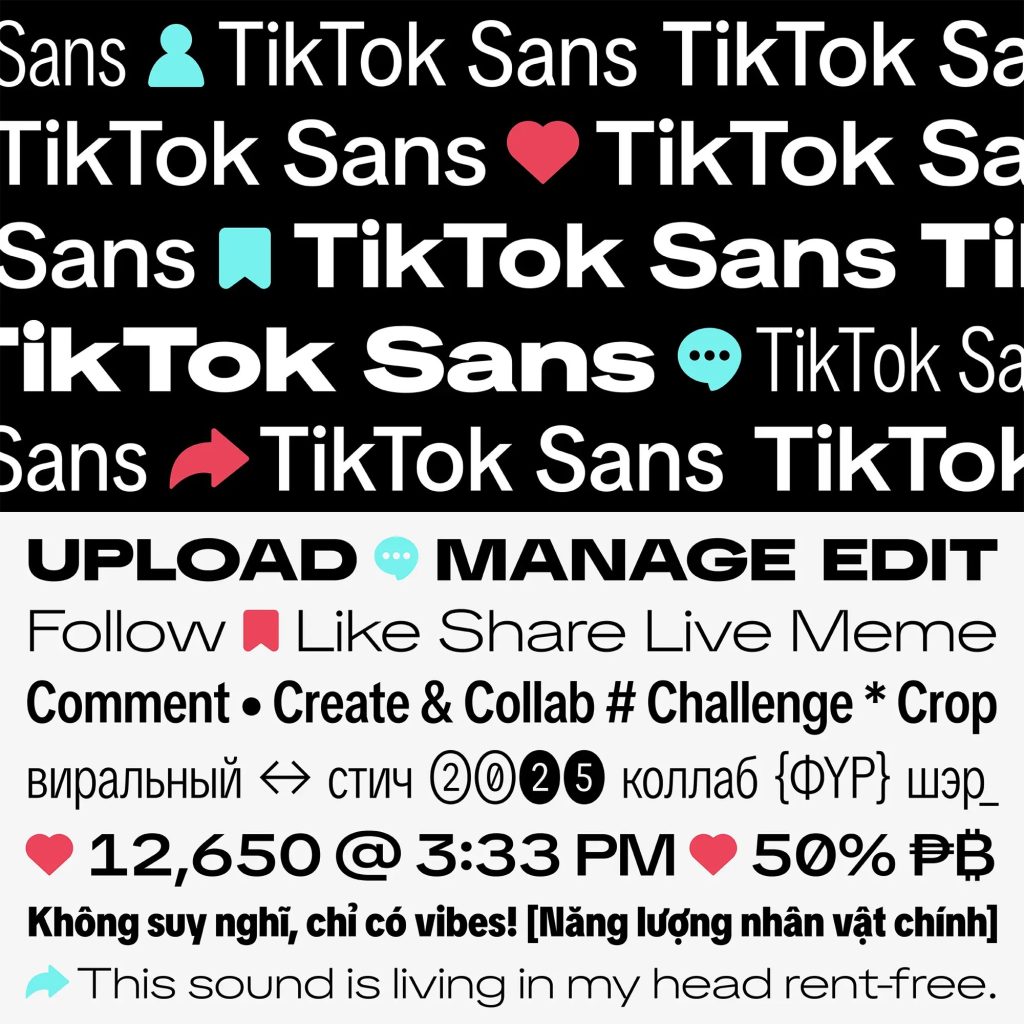
Martian Grotesk. Современный вариативный гротеск «Злых Марсиан» содержит 63 статичных начертания и изменяется по толщине и ширине. Оптимизирован для веба.
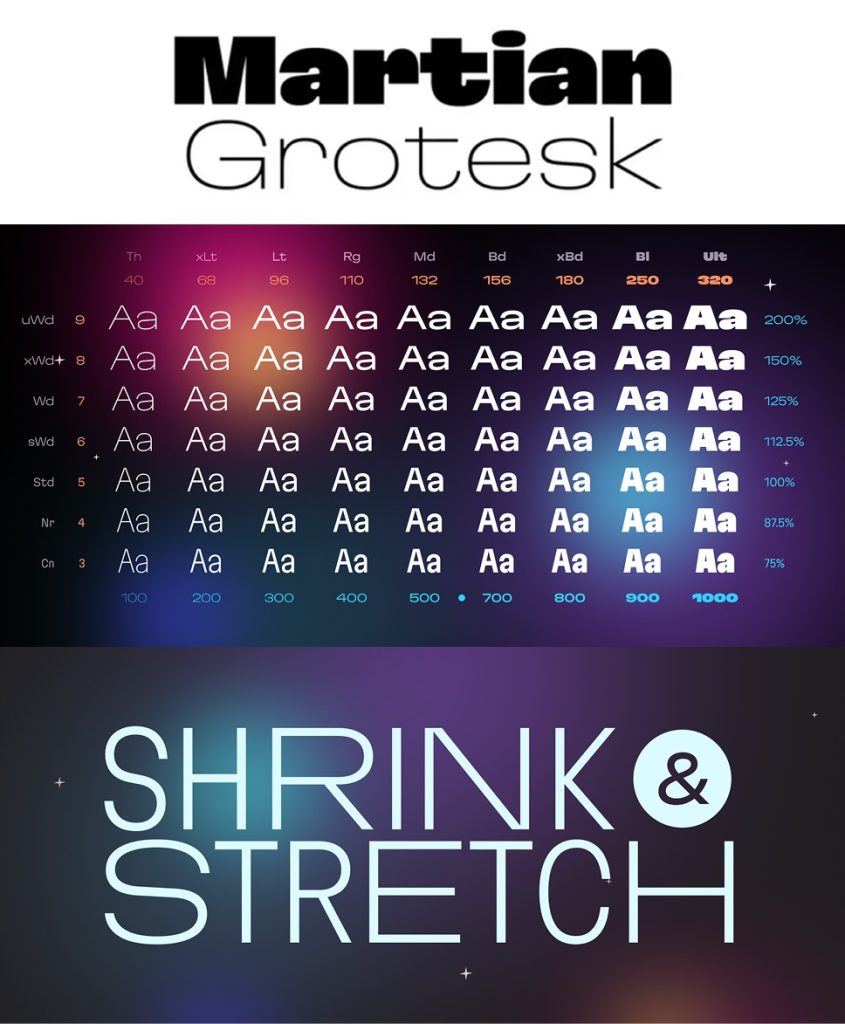
Лето. Вариативный декоративный гротеск с семью начертаниями и жизнерадостным характером.
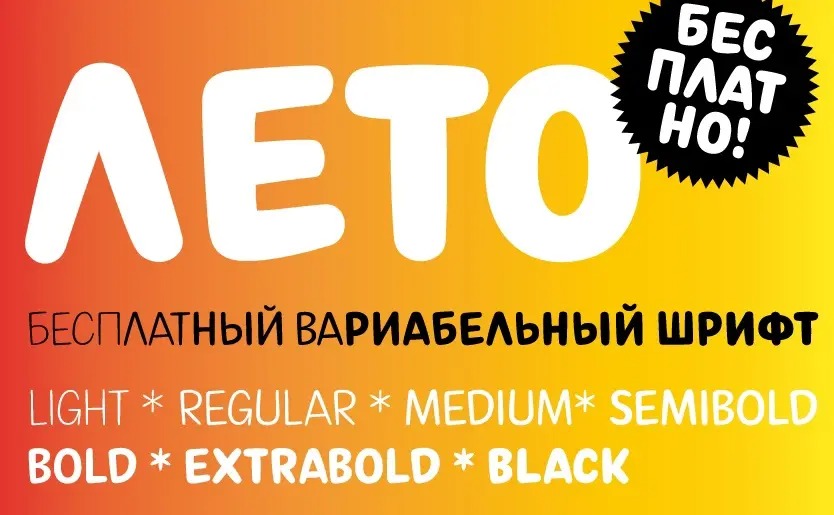
Noise. Лёгкий жизнерадостный гротеск в двух вариантах: базовом и со сплошными декоративными заливками. Подойдёт для упаковок, плакатов, брендинга и детских проектов.
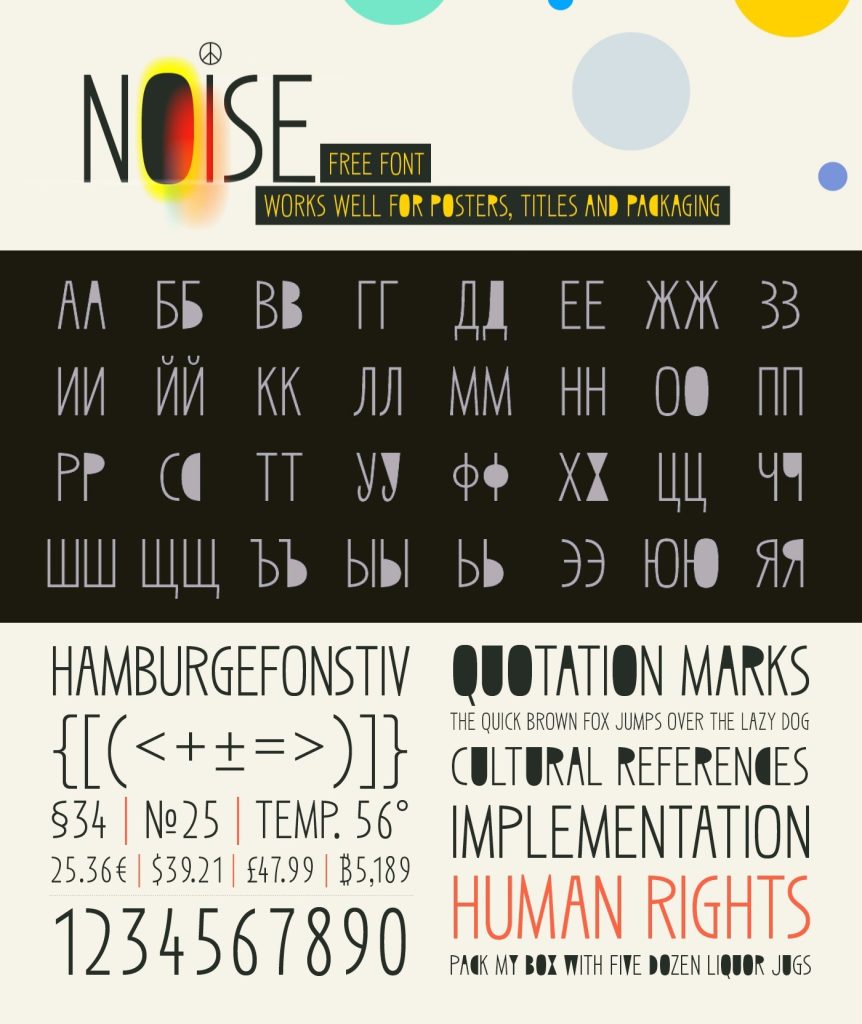
Martian Mono v1.1. Утилитарный шрифт для набора кода со специальными лигатурами, которые используют в языках программирования. Содержит четыре варианта ширины, в каждом из которых по семь вариантов насыщенности.
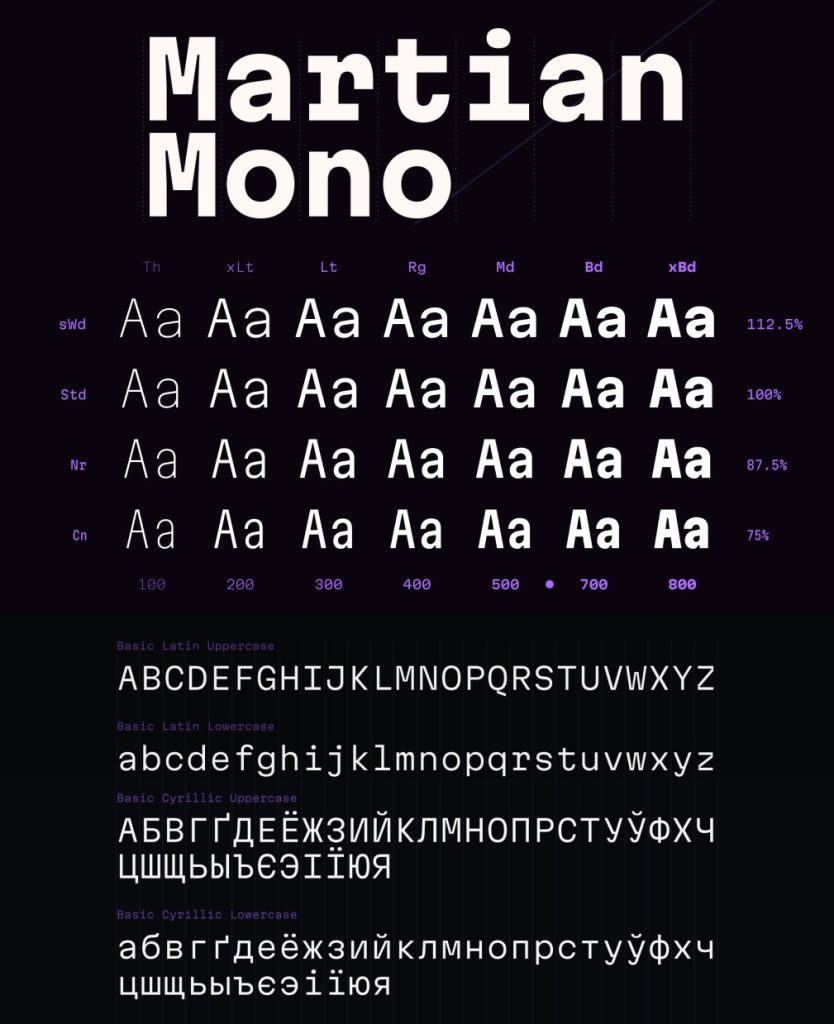
GOTHRA. Шрифтовая семья, разработанная на основе готического почерка. Гарнитура состоит из трёх начертаний, два из которых вариативные и одно статическое.
Подходит для заголовков, крупного набора, айдентики и плакатов.
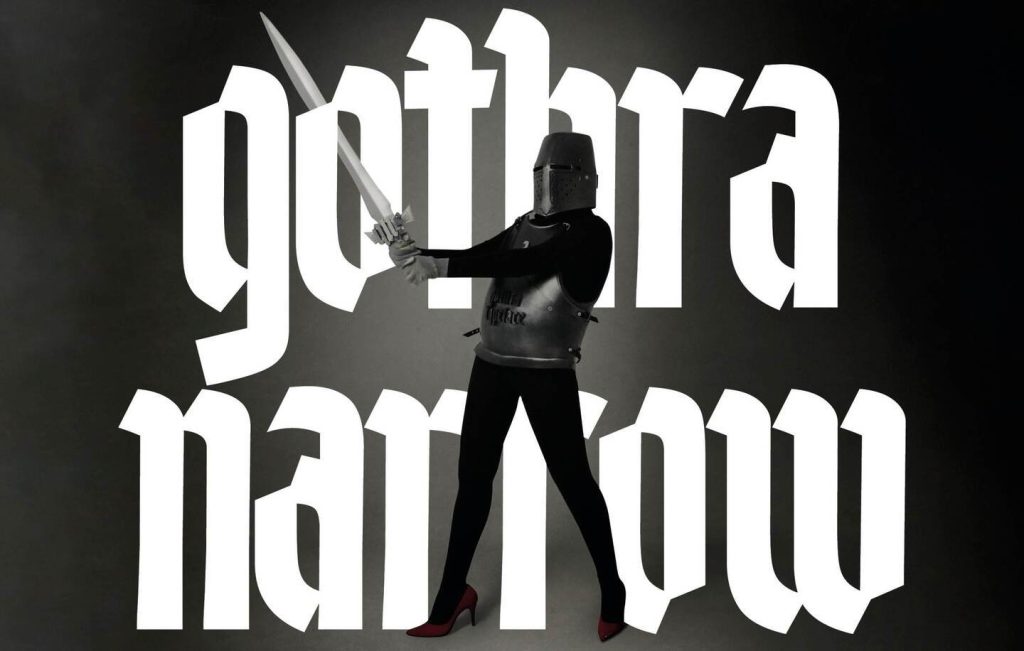
Dispater. Вариативный декоративный шрифт с пятью начертаниями, вдохновлённый эстетикой Средневековья. Его вытянутые, длинные символы с крупными «каплями» создают причудливый, сюрреалистичный узор.
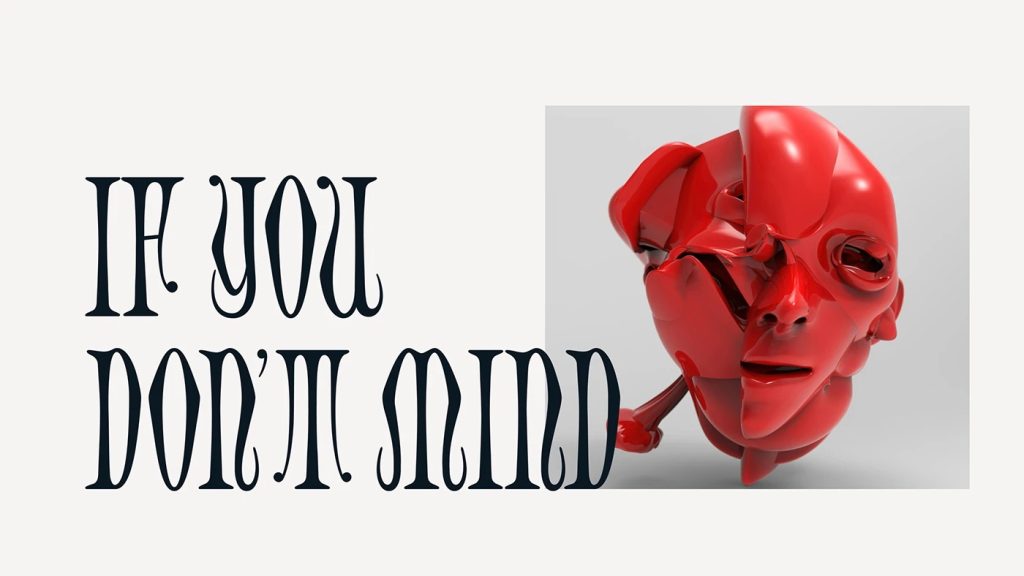
Извод. Акцидентный псевдостаринный шрифт в традиционном русском стиле.
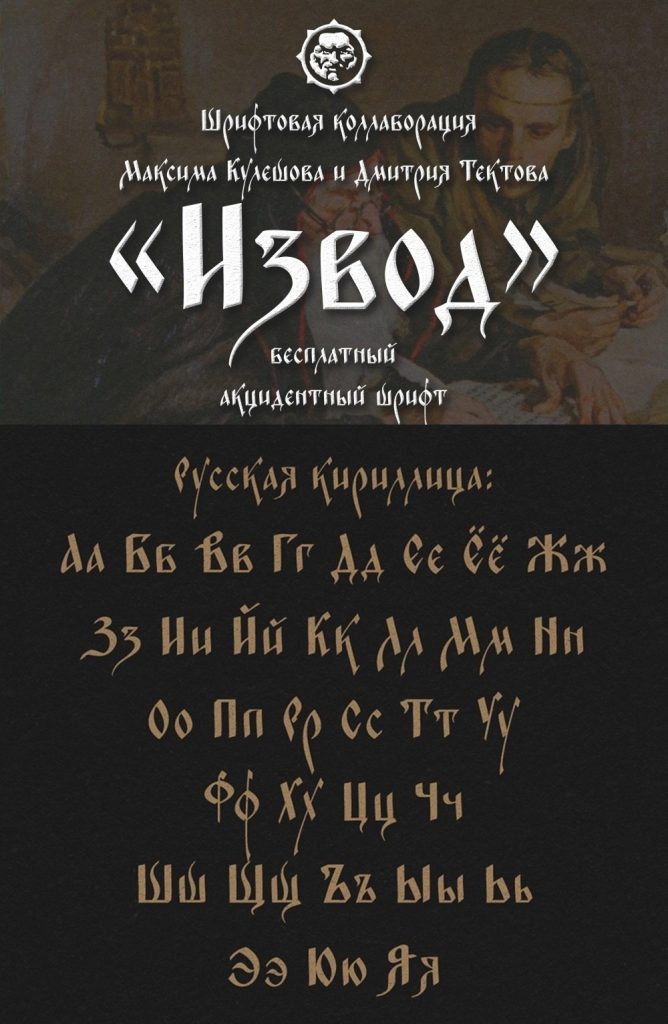
Siengfried. Акцидентная антиква с колючими засечками и обратным контрастом.
Доступны прямое начертание и курсив с обратным наклоном. В кассе знаков — латиница, кириллица и даже татарский алфавит.
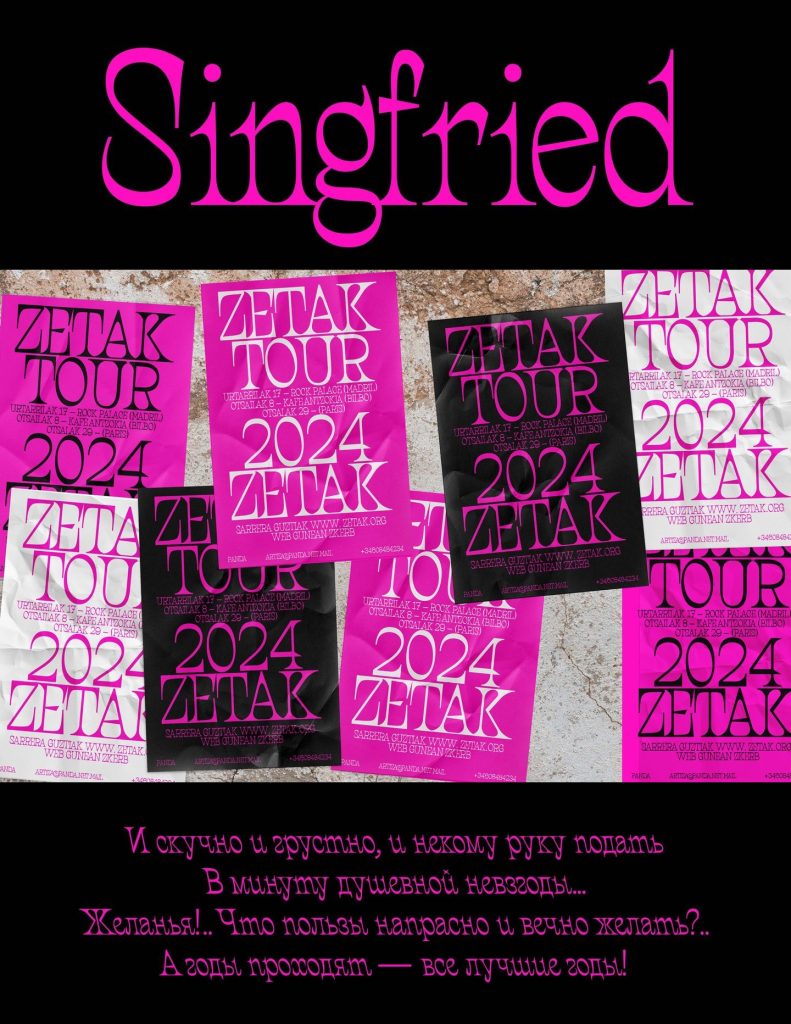
Gehaks. Акцидентная антиква с суровым характером, вдохновлена готическим стилем и скульптурами, вырубленными из камня. Имеет одно начертание и набор иконок.
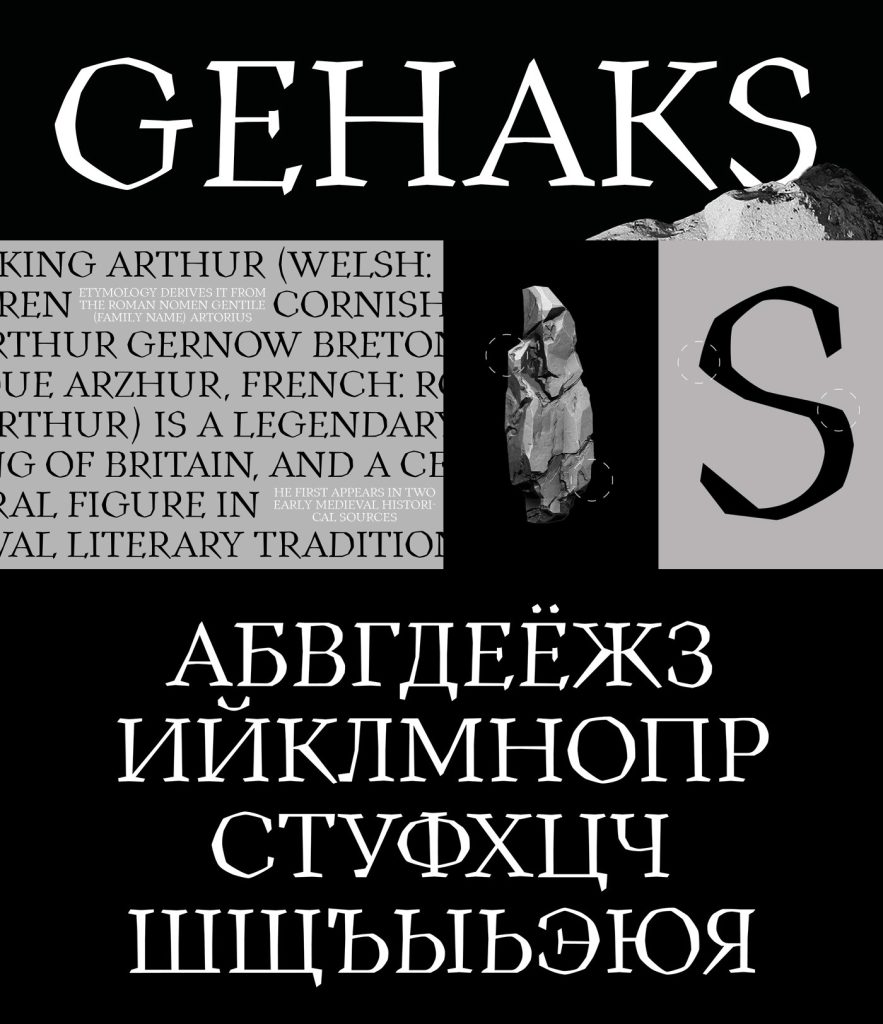
Буквоглот. Игривый декоративный шрифт с непохожими друг на друга буквами. Создан Кариной Кирилловой в рамках «Буквального челленджа».
Gergel. Дружелюбный шрифт, вдохновлённый детским рисунком.
Home Video. Псевдовинтажный декоративный пиксельный шрифт для ретропроектов, вдохновлённый меню на старых телевизорах. Буквы с нарочито небрежными формами отличаются по высоте — это имитирует текст интерфейса, который видеомагнитофоны выводили на экраны в 80–90-х годах.
Ножик. Выразительный декоративный шрифт с острыми, резкими формами. Подойдёт для плакатов, логотипов, заголовков или мемов.
Стежок. Декоративный шрифт, вдохновлённый алфавитами из схем по вышиванию. В основе шрифта — прописи XIX века, которые были пикселизированы.
Vivid Sans. Игривый акцидентный шрифт с чуть «гуляющими» толщинами и необычными скруглениями. Подойдёт для детских проектов или брендинга в сфере питания.